【ダイナフォント年間ライセンス「DynaSmart」まとめ記事】安いが許諾範囲が狭い「DynaSmart T」と高いが許諾範囲が安心の「DynaSmart V」を解説
DynaFont(ダイナフォント)シリーズは、TypeMuseumなどの売り切りのパッケージ製品の販売を終了しており、新規で購入する場合は年間定額制による「DynaSmart T」と「DynaSmart V」の2製品となっている。
「DynaSmart V」は、TrueTypeフォントもOpenTypeフォントに対応し、多言語フォントやWebフォントを含むダイナフォント全書体を収録している。また、印刷、Web、映像・動画、ゲームに許諾対応しているので、使用範囲が多岐に渡る場合、安心。「DynaSmart T」に比べて、かなり高いのがネックでプロデザイナー向き。定価は41,500円+税。
ダイナフォントの日本語書体TrueTypeフォント版を収録した、印刷物・ユーザー自身のWebサイトが使用許諾範囲内の年間ライセンス「DynaSmart T」はダイナフォントを安く使用したい場合にオススメ
DynaSmart Tは、ダイナフォントTrueTypeフォントWin版、Mac版書体をした年間ライセンス。
UDフォントやグッドデザイン賞受賞書体「古籍書体」も収録され、収録される日本語書体全書体に新元号「令和」の合字に対応。また、星座仮名フォントやアートフォントなど楽しい特典フォント2,400書体以上も収録。
「DynaSmart T」はビジネス資料作成にも適した読みやすい「UDフォント」を収録
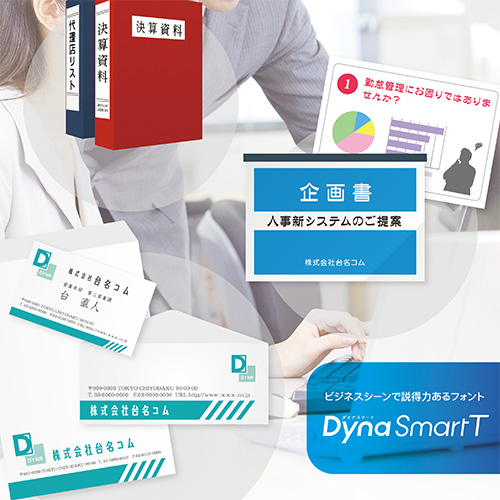
「DynaSmart T」には、誰にでも読みやすいフォントとして設計されたUDフォントを含む、複数の太さを持つ明朝体、ゴシック体、丸ゴシック体など基本書体を収録。
マイクロソフトの「Office」で作成するビジネス資料などで使用でき、読みやすいUDフォントや強調したい場面にオススメの極太フォントを駆使して説得力あるビジネス資料を作成することもできる。
年賀状や暑中見舞いなどプライベートシーンでは、収録されている楷書体、行書体、隷書体など豊富な毛筆系書体の使用がオススメ。
「DynaSmart T」は色々なデザインフォントでブランディングできる
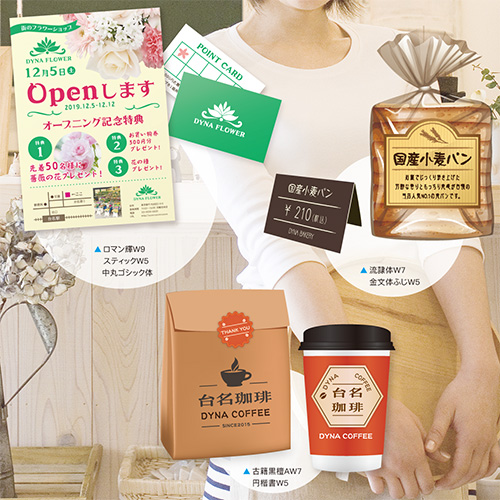
「DynaSmart T」はグッドデザイン賞受賞「古籍五書体」や「UDフォント」を収録
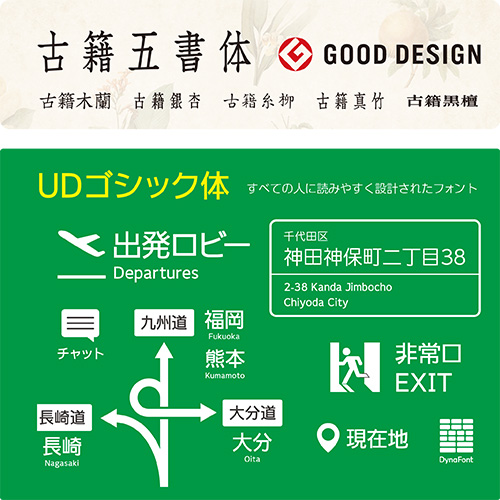
「DynaSmart T」は日本語書体が新元号「令和」の合字に対応
ダイナフォント年間ライセンス「DynaSmart T」に「雅風隷書体」「金文ゴシック体」が2019年5月28日に追加
DynaSmart Tに「雅風隷書体」「金文ゴシック体」の2書体が2019年5月28日に追加された。
「雅風隷書体」は、DF隷書体をベースにした隷書で、モダン・ライト・シンプルといったデザインエレメントを取り入れ書体。
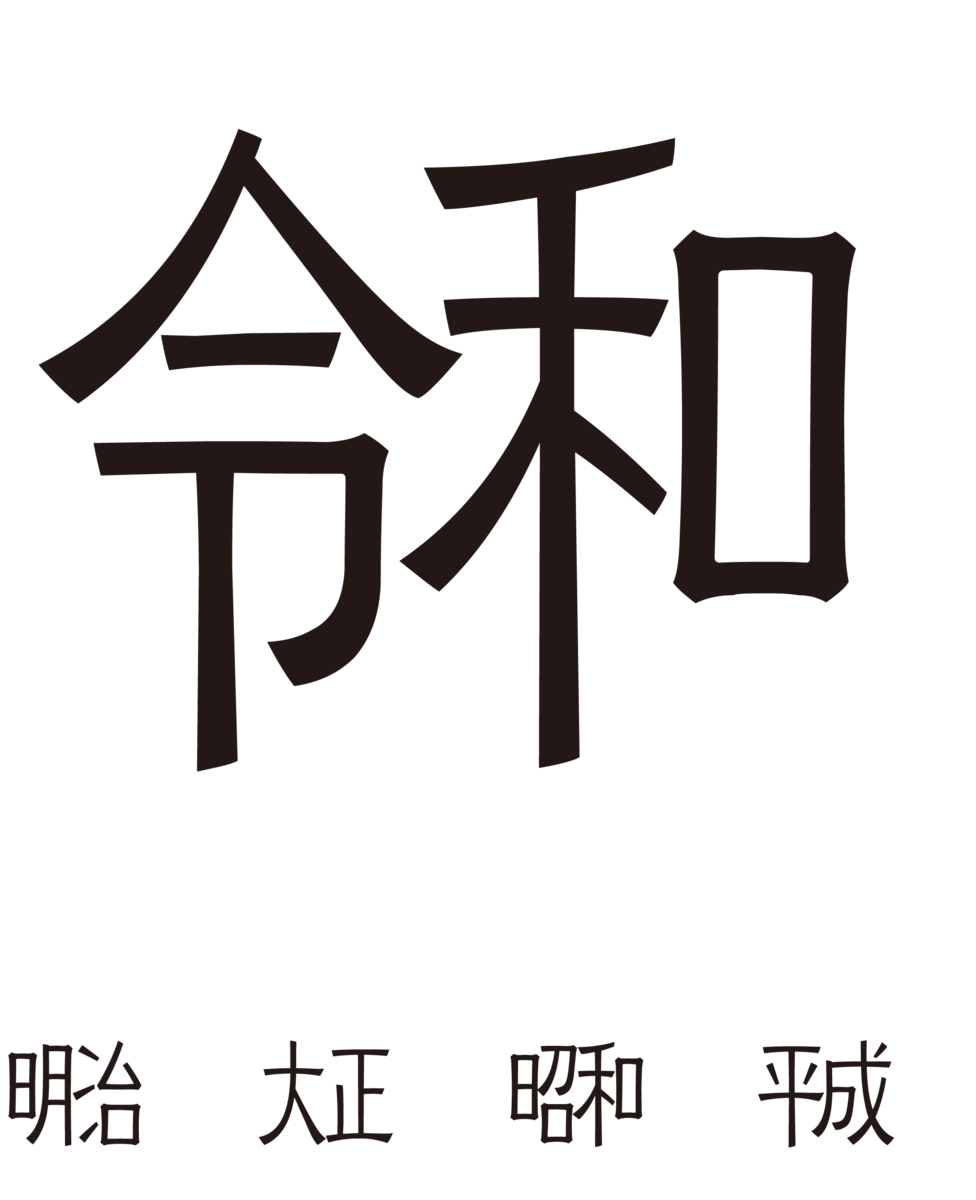
「金文ゴシック体」は、「金文体」をベースに、ゴシック体の角張りや太さの均一性といった特徴をブレンドした書体になっている。
「雅風隷書体」「金文ゴシック体」の2書体ともに新元号「令和」の合字も使用できる。
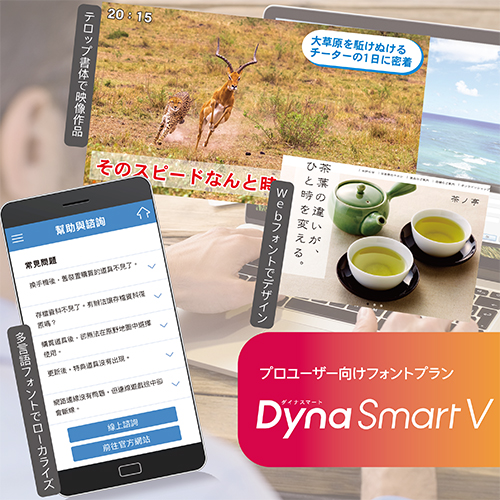
「DynaSmart V」は15種類の言語が使える「金剛黒体」など豊富な多言語フォントを収録
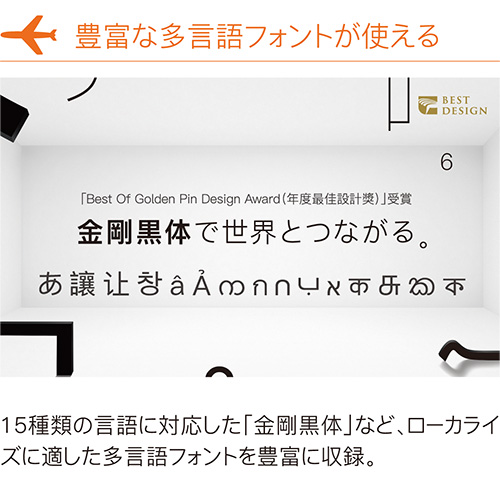
「DynaSmart V」は収録される日本語全書体が新元号「令和」の合字に対応
「DynaSmart V」はWebフォントクラウドサービス「DynaFont Online(DFO)」が使える
「DynaFont Online(DFO)」は、ダイナコムウェア株式会社が開発したWebフォントクラウドサービス。DFOを利用することで、金剛黒体を含むダイナフォント800書体以上が閲覧者の環境に依存することなくWebページ上で表示できる。もちろんWebフォントのメリットである、検索性の向上によるSEOの強化にもつながる。また、DFOを利用することで、画像に頼らないページデザインの構築が可能で、どのデバイスでも鮮明にテキストを表示でき、豊富な種類のフォントによる自由度の高いサイトを運用できる。DFOにはWebフォントを簡単な手順で導入できる4つのツールも提供される。
「青花ゴシック体」、「金剛黒体コンデンス」、「テロップ書体2書体」など112書体を2020年10月19日から「DynaSmart V」に提供開始
ダイナコムウェアは、ダイナフォント年間ライセンス「DynaSmart V」「DynaSmart 教育機関向けプラン」「DynaSmart 学生版」ユーザーに向けて、2020年10月新書体「青花(せいか)ゴシック体」「金剛黒体(こんごうこくたい)コンデンス」、テロップ書体「娥眉(がび)明朝体S」「POPミックスS」を含むダイナフォント112書体を2020年10月19日(月)より提供した。
「DynaSmart V」はWebなどデジタルデザインに最適な「青花ゴシック体」、4種類の横幅×6ウェイトのコンデンス書体の追加でますます使いやすくなる「金剛黒体」、2種類の「テロップ新書体」など、豊富な追加ラインナップ書体で、デザインの可能性をさらに広げていく。
〇新元号「令和」合字対応版書体に関して
先行して提供したTrueTypeフォント版に続き、この度のバージョンアップにより、DynaSmartシリーズで提供しているOpenTypeフォントStd、OpenTypeフォントStdN、OpenTypeフォントPro-5、OpenTypeフォントPro-6、OpenTypeフォントPro-6N全ての日本語が新元号「令和」の合字に対応となった。